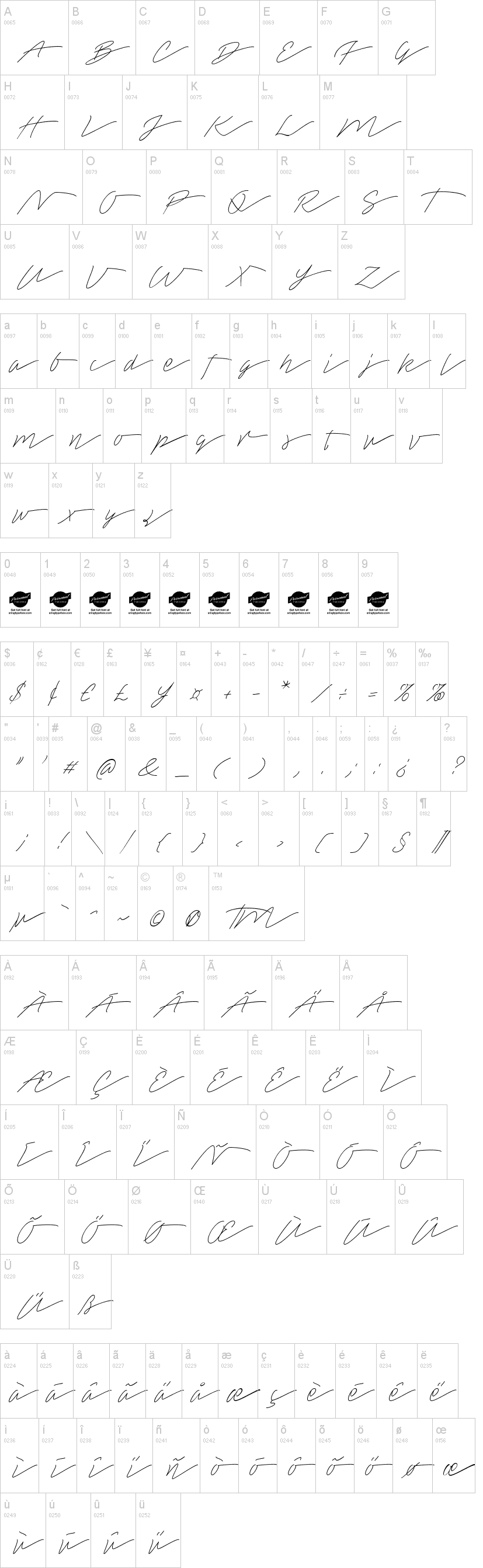
? Tamoro Script 是一款自然的手写脚本字体,它拥有自然的手写风格,清晰的细节,甚至可以模仿真实的手写风格。它可以用于创建浪漫的、精致的、生动的文字,可以应用于卡片、海报、标题、标签等等。它还支持多种语言,可以让你的文字更加有趣、富有个性。内容介绍
Tamoro Script是一款非常不错的手写艺术字体,具有很好的视觉感,适合于文化类的宣传设计、商业类品牌的广告和产品包装设计以及个性化文字排版等较多场景。